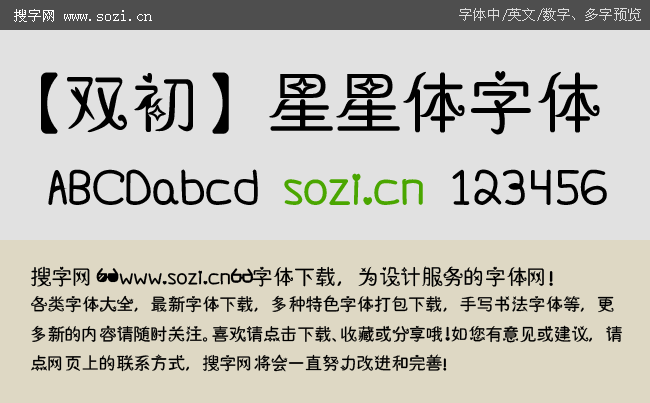
星星體字體
搜字網(wǎng)給大家提供一款很卡通的手機(jī)中文字體下載。修改者給這款字體叫星星體字體,這款字體以漢儀秀英體為原形,并配上可愛的卡通星星等圖案,漢儀秀英體單字的點(diǎn)是心形桃點(diǎn),短撇為飄動(dòng)的柳葉形,非?蓯。該中文字體趣味性強(qiáng),非常適合喜歡卡通的朋友在手機(jī)上安裝使用。